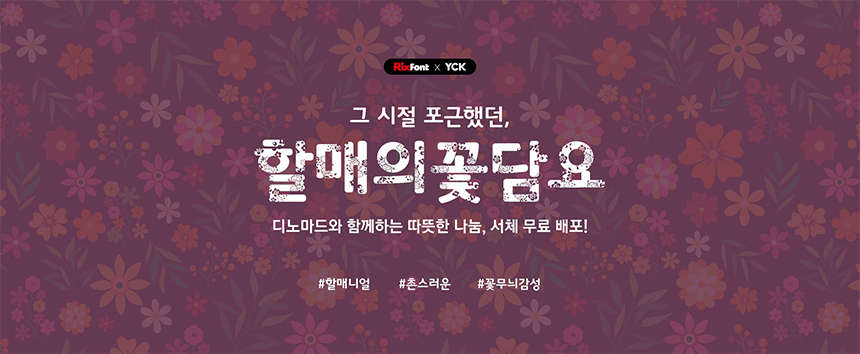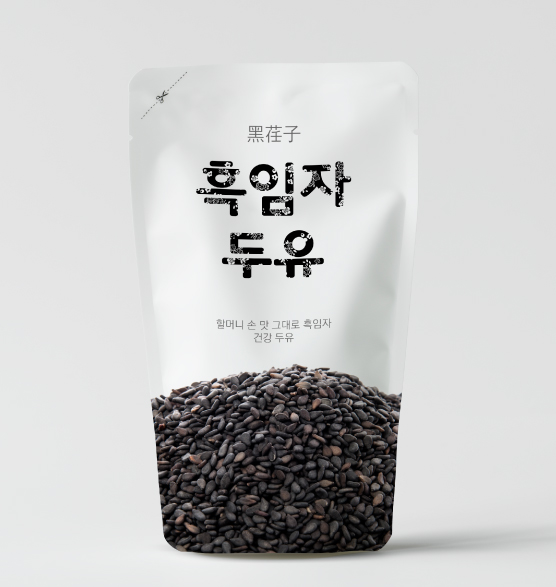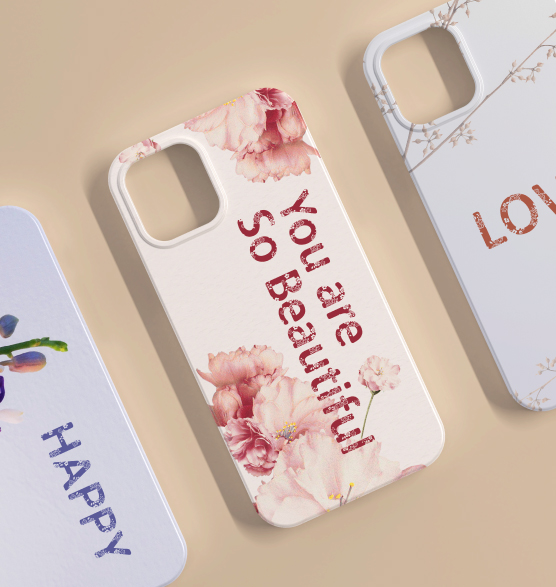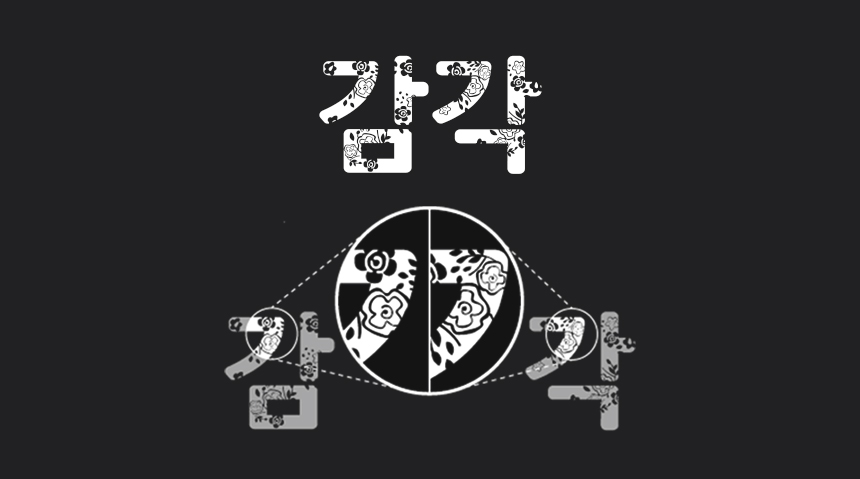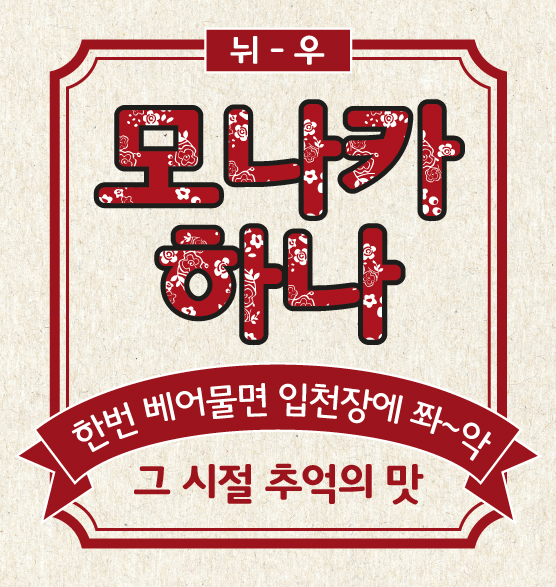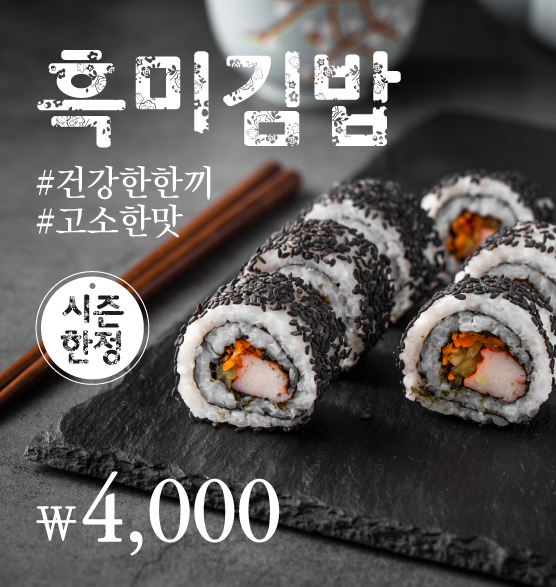
할머니의 꽃무늬 담요
어린 시절 시골에 가면 항상 함박웃음으로 맞아주셨던 할머니의 모습이 떠오릅니다. 추운 날 가장 뜨끈한 아랫목에 나를 앉히고 포근한 이불을 덮어주셨던 기억. 그 오색찬란했던 꽃무늬 이불은 참 촌스러웠는데 지금 생각해 보면 사랑으로 덮어준 담요가 무엇보다 따뜻했던 기억뿐입니다. 빛바랜 추억 속 할머니의 꽃무늬 담요가 생각나는 서체. 촌스럽지만 따뜻한 감성 가득한 폰트를 소개합니다.
Rix할매의꽃담요 서체는 현재를 살아가며 잊혀가는 옛 기억 속 따스함과 포근함을 담은 서체입니다. 디노마드@yck_kr와 함께하는 따뜻한 나눔 캠페인의 일환으로 누구나 제약 없이 사용할 수 있도록 무료로 배포합니다.
폰트는 사랑을 싣고
할머니 방 한편에 켜켜이 쌓여있던 화려한 꽃무늬 이불을 기억하시나요? Rix할매의꽃담요는 할머니의 형형색색 색동 이불과 자기주장 강한 꽃들이 수 놓인 무늬들을 표현한 서체입니다. 또한 어린 시절 할머니가 덮어준 담요의 포근함과 따스함을 담아 모든 것이 빠르고 현대화된 시대 속에서 흐릿해지는 것들을 추억하게 합니다.
꽃을 품은 제목용 서체
Rix할매의꽃담요는 특징적인 패턴으로 개성 있고 주목성이 높은 서체입니다. 일반적인 서체들과 다른 독특한 디자인으로 어떤 컨셉으로 연출되느냐에 따라 무수히 다른 느낌을 낼 수 있습니다. 패키지, 제품 등 메인에 들어가는 문구를 강조할 때, 밋밋한 디자인에 포인트를 줄 때 활용하기 좋습니다.
Rix할매의꽃담요 서체의 기본 형태는 Rix밝은굴림 폰트의 4가지 웨이트 중 가장 두꺼운 웨이트(Extra Bold)와 동일합니다. 두께감 있는, 큰 자소를 가진 굴림체의 친근하고 부드러운 형태와 꽃을 품은 패턴이 만나 제목용 서체로 활용하기에 최적의 조건을 갖추었습니다.
연속되지 않는 패턴
같은 자음도 모음 배열 기준에 따라 패턴의 모양이 달라져 문장 조합 시 사용자는 다양한 느낌을 연출할 수 있습니다. 아무래도 폰트에 패턴을 넣어 제작하는 것 자체가 굉장히 어려운 작업이고 용량이 너무 커지는 이슈도 있었어요. 그럼에도 자소 하나하나에 적절한 무늬를 넣는 동시에 연속되지 않도록 만들어야 했기에 더욱 난이도가 높은 작업이었습니다.
긴 시간에 걸쳐 작업한 결과 완성도 높은, 어디에도 없는 특별한 꽃을 담은 서체가 탄생했습니다.
| 이렇게 사용해 보세요
요즘 #할매니얼 감성이 하나의 트렌드로 떠오르고 있는데요. 이런 트렌드에 맞는 촌스러운 듯 레트로한 콘텐츠에 잘 어우러지는 폰트입니다. Rix할매의꽃담요와 기본 형태가 같은 Rix밝은굴림 서체와 함께 조합하여 다양한 디자인에 활용해 보세요.